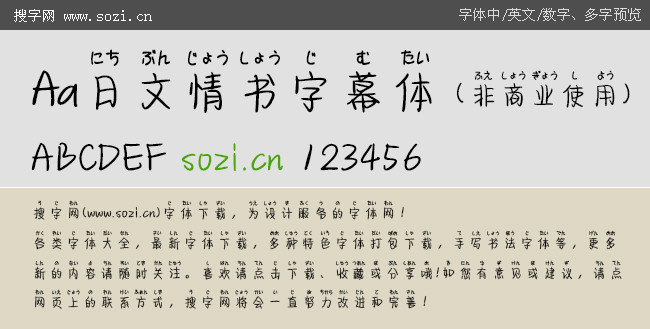
Aa日文情書字幕體
搜字網(wǎng)給大家提供一款A(yù)a日文情書字幕體(非商業(yè)使用)中文字體下載,該字體是一款手寫書法字體,字體筆觸纖細(xì),書寫流暢,字形灑脫,具有很好的視覺感,合應(yīng)用于藝術(shù)設(shè)計(jì)、平面宣傳設(shè)計(jì)、網(wǎng)頁設(shè)計(jì)、海報(bào)設(shè)計(jì)等應(yīng)用(此字體為個(gè)人非商用版,商用可以聯(lián)系QQ:1006760504)。